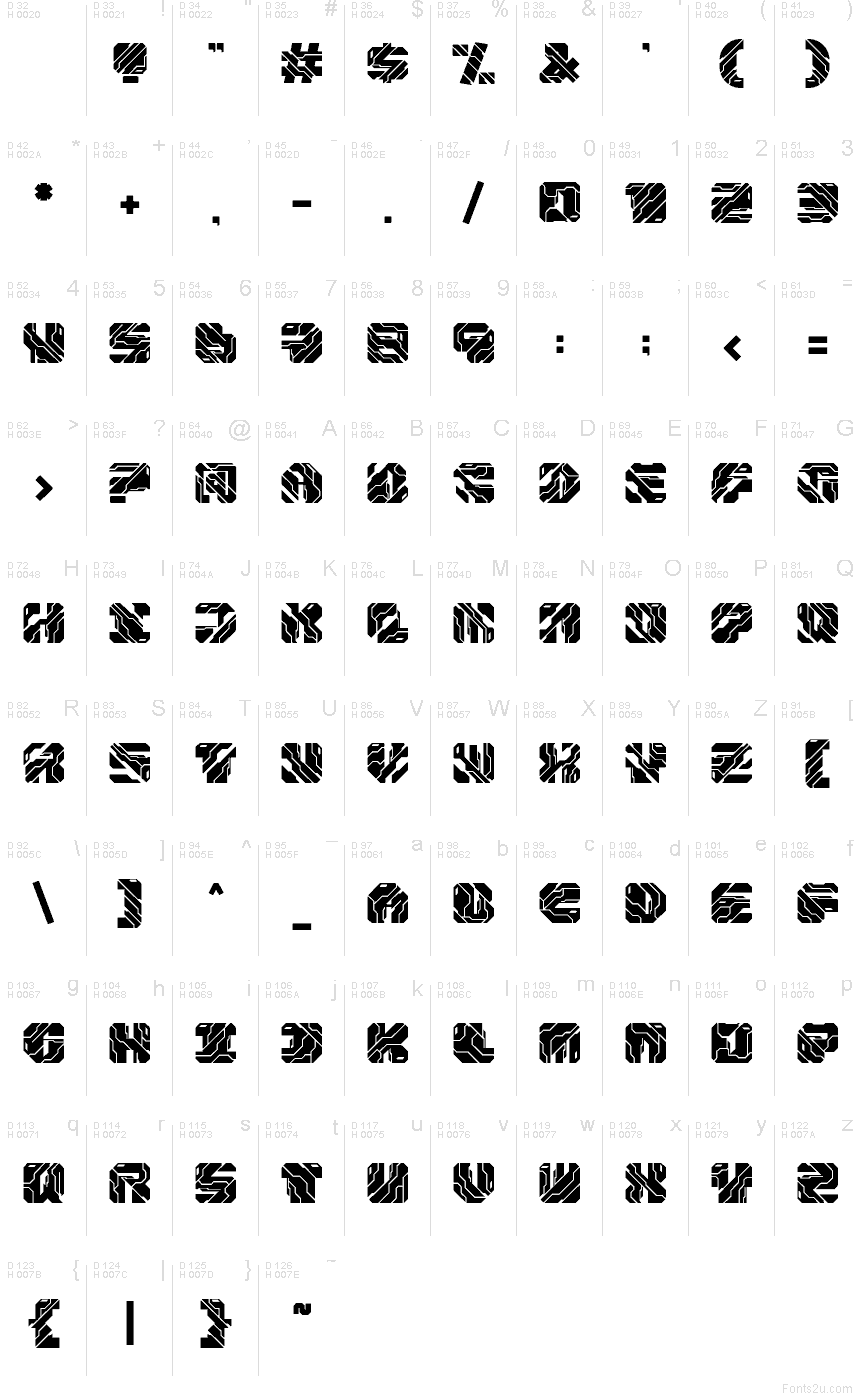
Space Sparkle One od Putracetol Studio je bezplatné sci-fi písmo typu display, jehož blokové siluety jsou vyřezány do vrstvených cest připomínajících obvody. Toto opakované členění dává písmenům texturu mechanického povrchu, díky čemuž design působí jako součást displejů, konzolí a vesmírných technologií, nikoliv jako běžné geometrické písmo.
Skvěle se hodí pro názvy her, esportový branding, nadpisy plakátů, obaly alb a streamovací overlaye, kde ostré vnitřní výřezy doplňují panely uživatelského rozhraní a digitální cesty. Krátké texty na obalech a grafika technologických akcí také těží z jeho kompaktní, segmentované hmoty, která vytváří silný grafický otisk bez nutnosti dalších efektů.